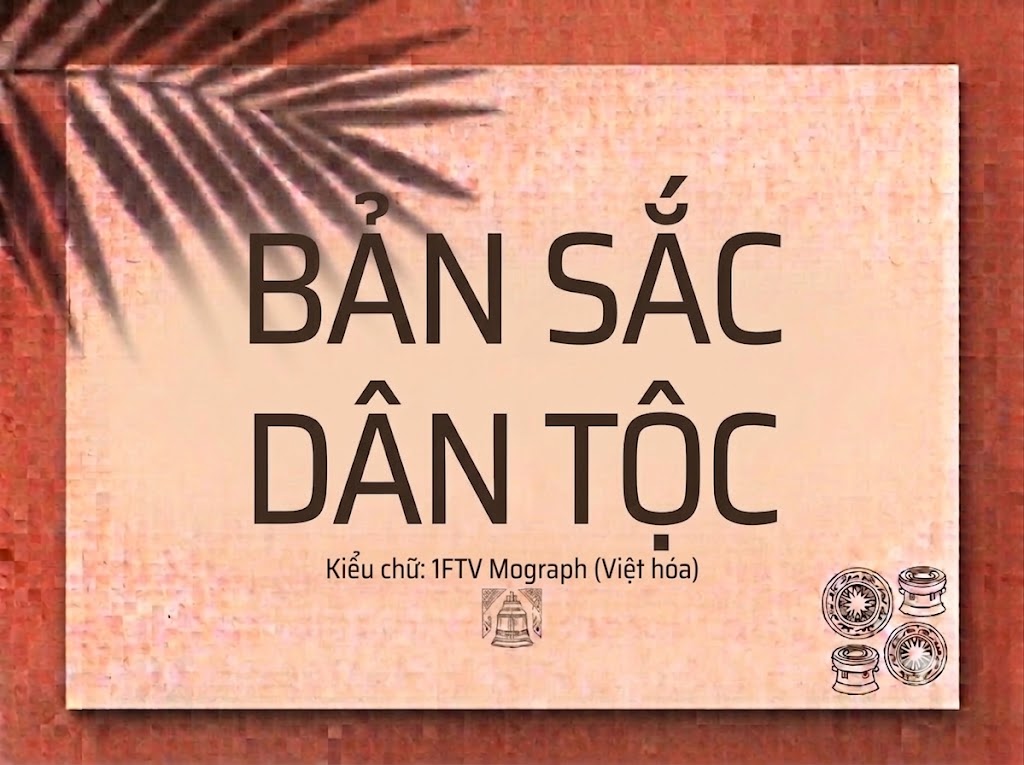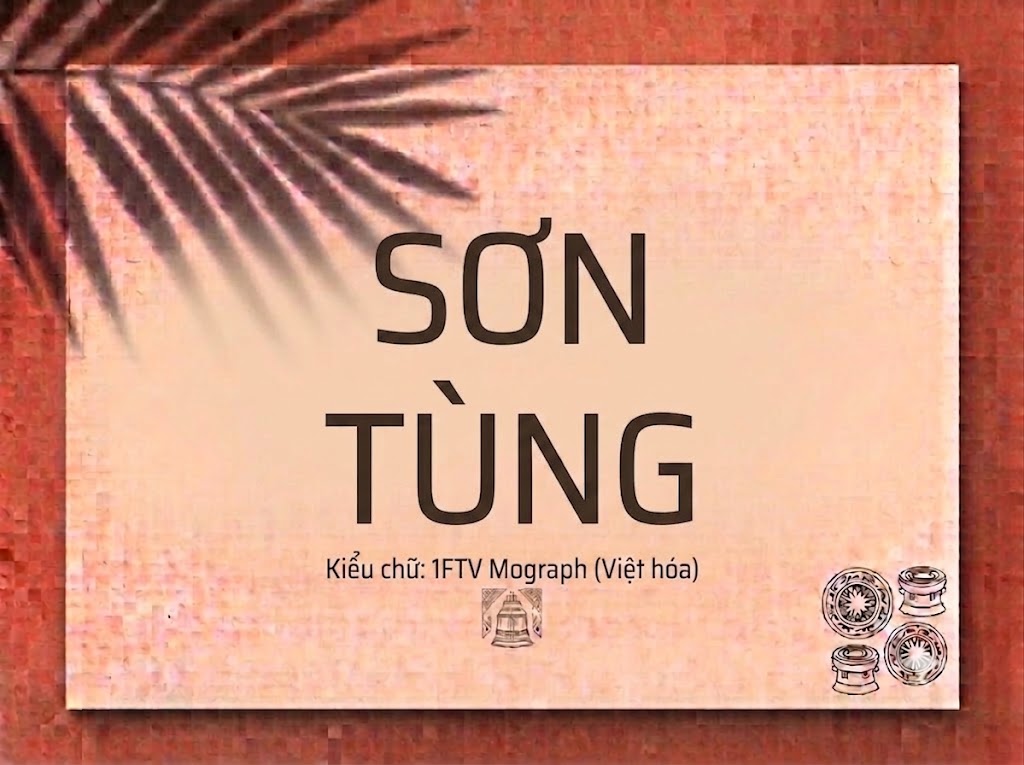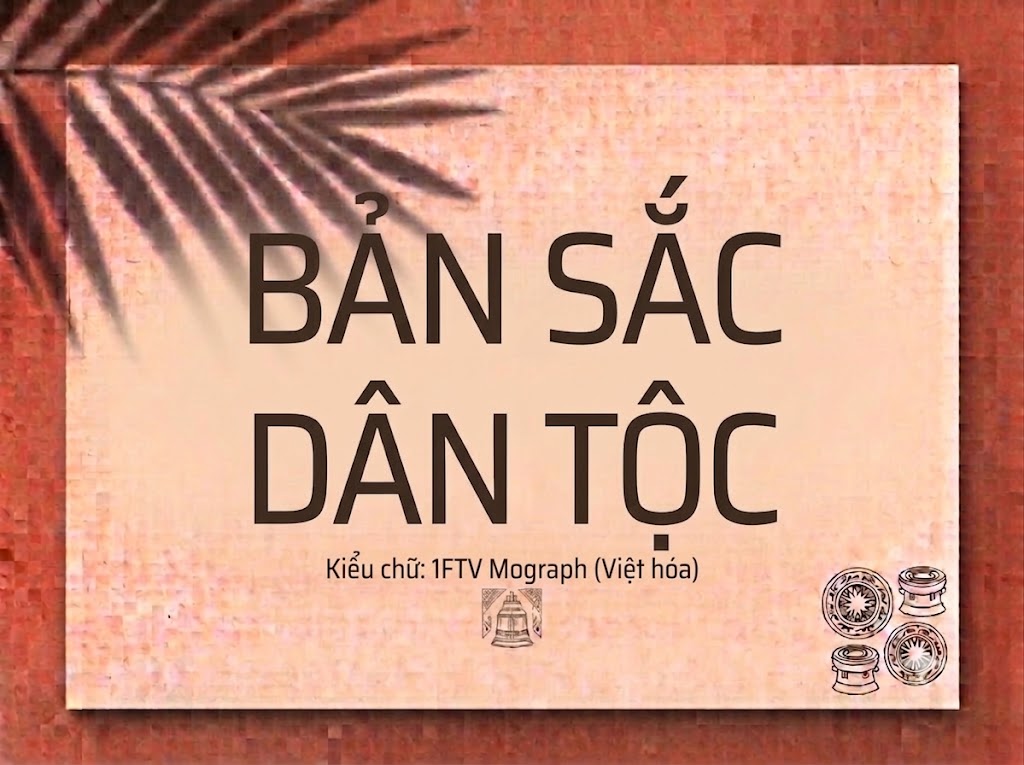
1FTV Mograph
Trong xu hướng thiết kế đồ họa kỹ thuật số hiện nay, các phông chữ không chân mang phong cách hình học luôn được các nhà sáng tạo săn đón hàng đầu. Nhờ kết cấu tinh gọn, cân đối và hiện đại, kiểu chữ này không chỉ giúp tối ưu hóa không gian hiển thị mà còn đem lại cảm giác chuyên nghiệp, dễ chịu cho người xem trên mọi loại màn hình.
Nếu bạn đang tìm kiếm một bộ chữ đa năng, sở hữu những đường nét bo cong tròn trịa chuẩn mực để làm tiêu đề, phụ đề video ngắn hay các ấn phẩm truyền thông hiện đại, thì font 1FTV Mograph chính là sự lựa chọn lý tưởng.
Giới thiệu về font 1FTV Mograph
Font 1FTV Mograph là một bộ chữ hiển thị không chân được xây dựng trên nền tảng tỷ lệ hình học phẳng, hướng tới sự tinh giản tối đa và tính ứng dụng cao trong môi trường thiết kế chuyển động cũng như kỹ thuật số.
Nhờ cấu trúc kỹ thuật đồng bộ, phông chữ mang lại khả năng hiển thị mượt mà trên mọi độ phân giải. Bạn có thể thoải mái co giãn, phóng lớn chữ trên các phần mềm đồ họa chuyên nghiệp mà không lo gặp lỗi vỡ nét hay răng cưa.
Đặc điểm nổi bật
Sức hút lớn nhất của font 1FTV Mograph đến từ nét vẽ tối giản nhưng có độ hoàn thiện rất cao trong cấu trúc hình khối:
Tỷ lệ hình học rõ ràng: Các ký tự có đường cong như o, c, d, p, q được tạo hình theo những đường tròn chuẩn mực, tạo cảm giác không gian chữ luôn thông thoáng, rộng rãi và mang hơi hướng công nghệ hiện đại.
Độ dày nét đồng đều: Khoảng cách giữa nét thanh và nét đậm hầu như không có sự chênh lệch. Cấu trúc đồng nhất này giúp cải thiện tối đa độ rõ nét của văn bản khi nhìn từ xa hoặc khi hiển thị lướt qua trên màn hình.
Hỗ trợ hoa và thường linh hoạt: Bộ chữ tích hợp đầy đủ hệ thống chữ cái viết hoa và viết thường đồng bộ, cho phép các designer dễ dàng phân tầng nội dung chính phụ một cách tự nhiên trên cùng một khung hình.
Để phông chữ vận hành hoàn hảo trên các hệ điều hành phổ biến từ Windows đến macOS, phiên bản Việt hóa này đã được tinh chỉnh kỹ lưỡng về các thông số nội tại:
Hệ thống khoảng cách giữa các chữ và độ giãn dòng được căn chỉnh chuẩn xác đến từng pixel, đảm bảo các khối ký tự đứng cạnh nhau luôn giữ được khoảng trống thẩm mỹ lý tưởng, không bị dính nét khi gõ tiếng Việt có dấu.
Tích hợp đầy đủ dãy chữ số từ 0-9 dáng đứng tinh gọn cùng hệ thống các ký tự đặc biệt, dấu câu thông dụng như .:,;'”(!?)+-*/=.
Bản Việt hóa chuẩn chỉnh giúp bạn hoàn toàn yên tâm thiết kế các nội dung truyền thông dài mà không sợ gặp phải tình trạng nhảy font hay lỗi hiển thị dấu câu khó chịu.
Hình ảnh demo thực tế
Để dễ dàng đánh giá khả năng hiển thị trực quan của phông chữ này trên các tỷ lệ kích thước khác nhau, bạn có thể tham khảo bảng mô phỏng từ file hệ thống image_c676ff.png:
Kích thước nhỏ (12pt – 24pt): Bộ chữ viết thường và chữ số vẫn hiển thị ngay ngắn, rành mạch và cực kỳ dễ đọc ngay cả trên màn hình thiết bị di động cỡ nhỏ.
Kích thước lớn (36pt – 72pt): Đây là không gian lý tưởng nhất để font phô diễn nét tinh tế, tròn trịa của cấu trúc hình học, tạo tác động thị giác sạch sẽ và chuyên nghiệp cho các dòng headline chính.
Ứng dụng trong thiết kế đồ họa và làm video
Sở hữu nét cá tính tối giản, sạch sẽ và cấu trúc hoa – thường linh hoạt, font 1FTV Mograph mở ra không gian ứng dụng rộng lớn cho các dự án truyền thông thế hệ mới:
Làm tiêu đề và phụ đề video ngắn (TikTok, Reels, Shorts): Dáng chữ đứng ngay ngắn, rõ nét cực kỳ hoàn hảo cho các khung hình dọc tỷ lệ 9:16. Độ rõ ràng của nét chữ giúp lời thoại phụ đề hiển thị một cách tự nhiên, cuốn hút người xem lướt bảng tin dừng lại mà không che khuất các chủ thể chính của video.
Thiết kế ảnh thu nhỏ mạng xã hội (Thumbnail): Lựa chọn tuyệt vời cho các thumbnail YouTube, TikTok quảng cáo sản phẩm, nội dung công nghệ, vlog đời sống hoặc chia sẻ kiến thức nhằm bứt phá tỷ lệ nhấp chuột nhờ độ hiển thị trực diện từ khoảng cách xa.
Banner quảng cáo sản phẩm và giao diện UI/UX: Hoàn hảo cho các poster giới thiệu sản phẩm công nghệ, ứng dụng di động, đồ gia dụng thông minh hoặc thiết kế website cần sự tinh tế, ngăn nắp và hiện đại.
Nhận diện thương hiệu tối giản: Phù hợp làm logo dạng chữ khối, biểu ngữ quảng cáo hoặc thiết kế nhãn mác cho các studio sáng tạo hướng tới tệp khách hàng trẻ tuổi.